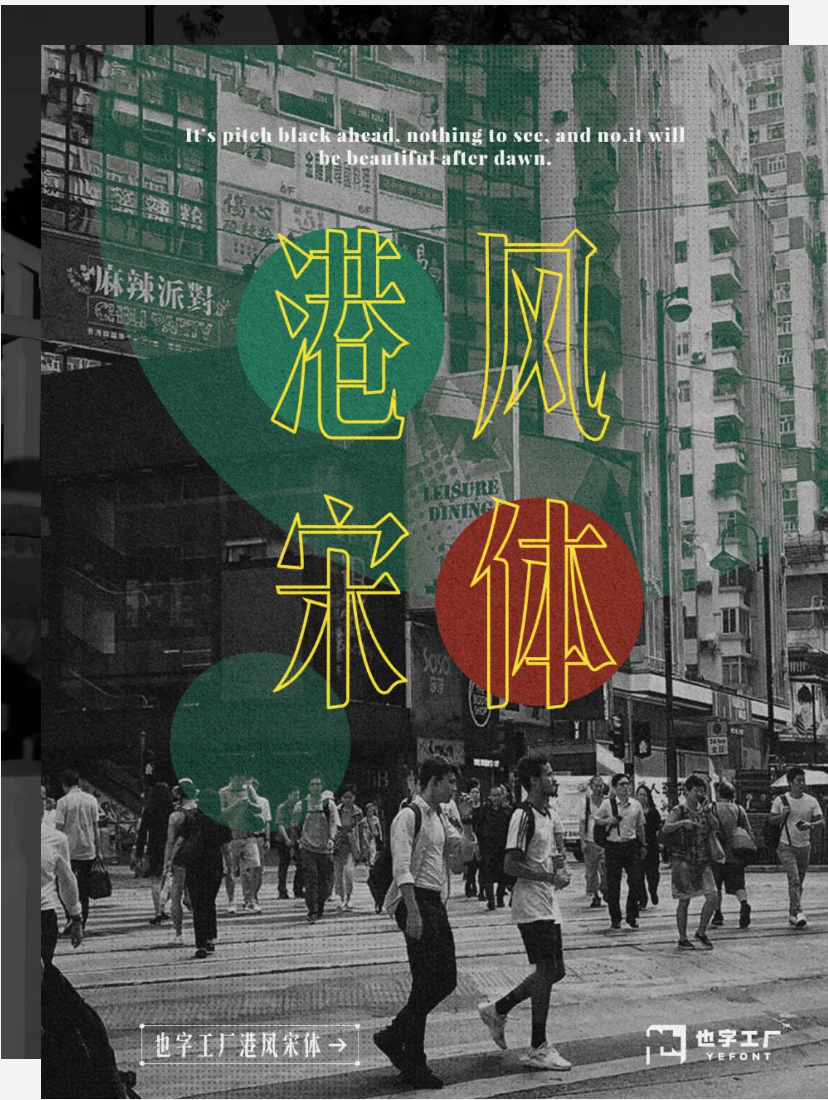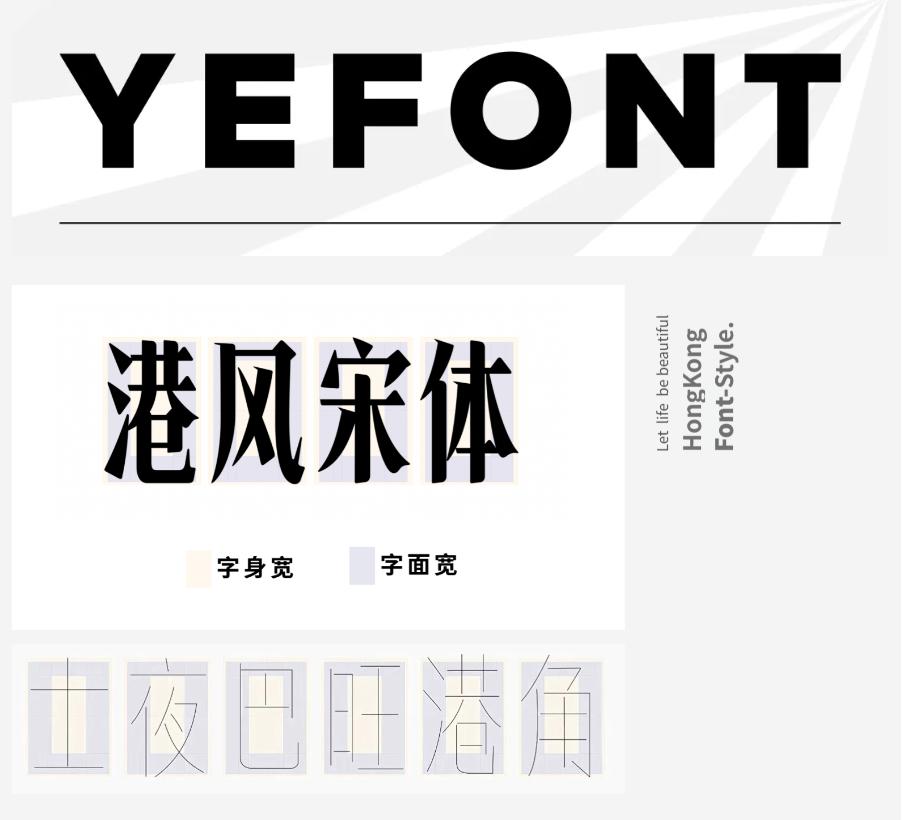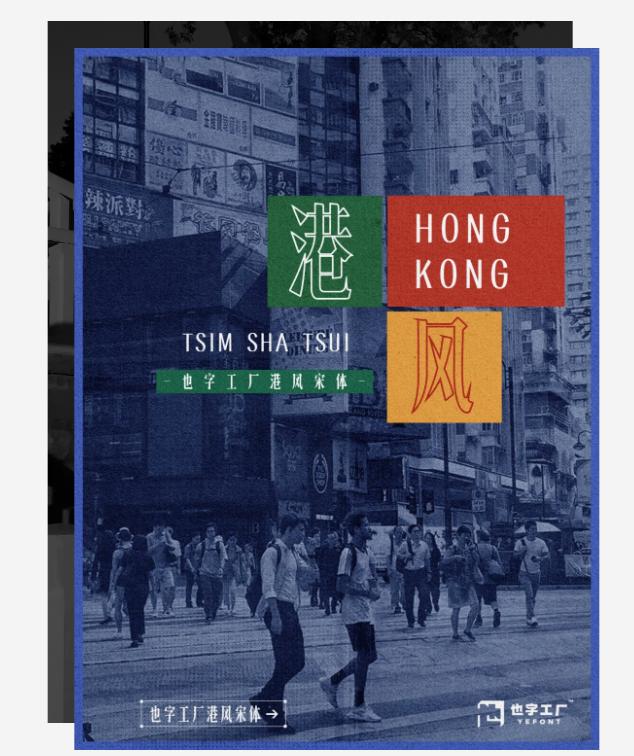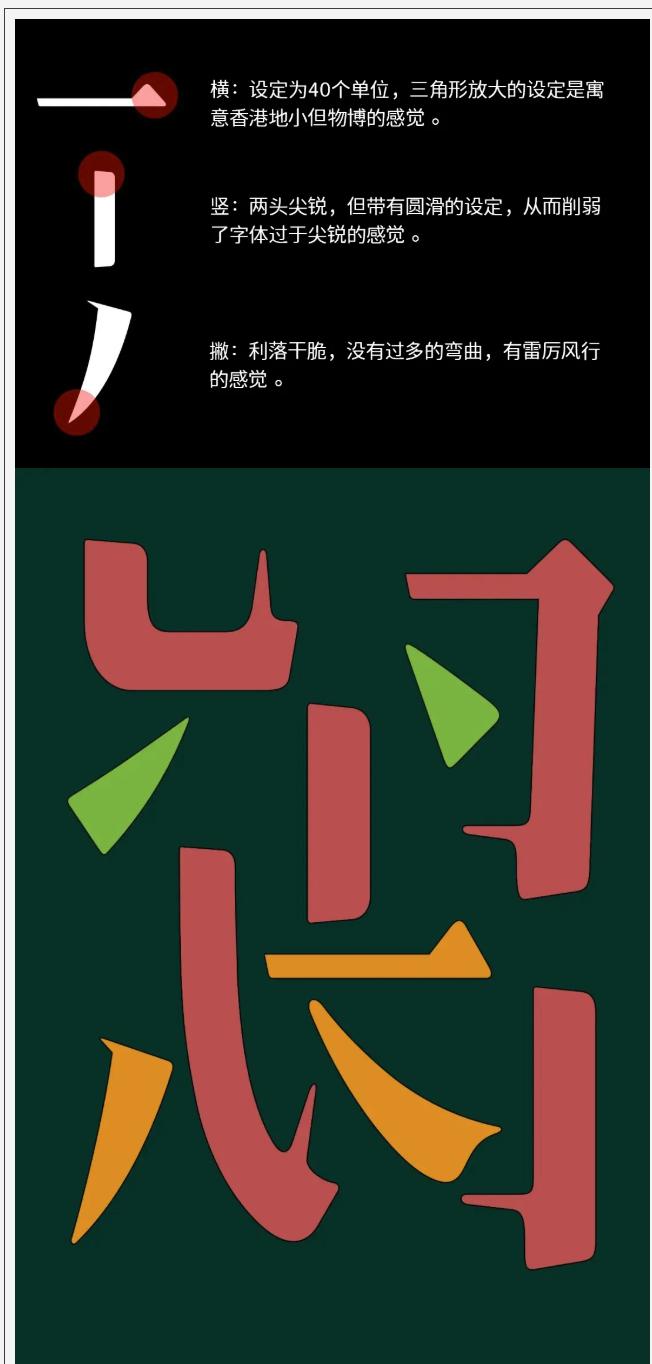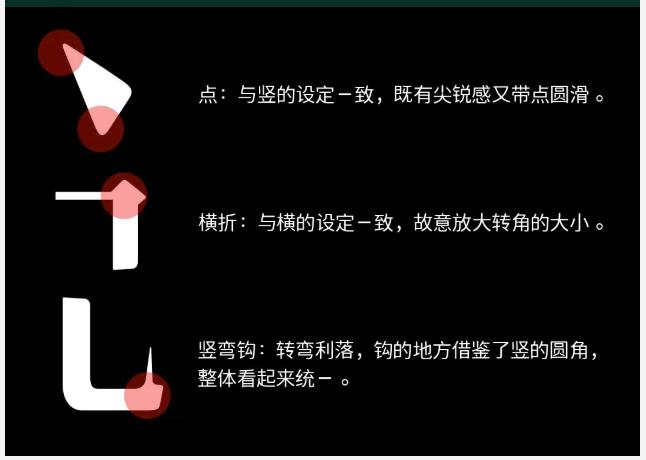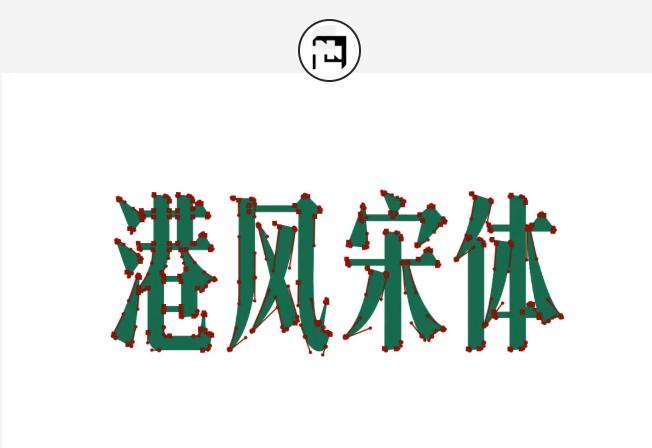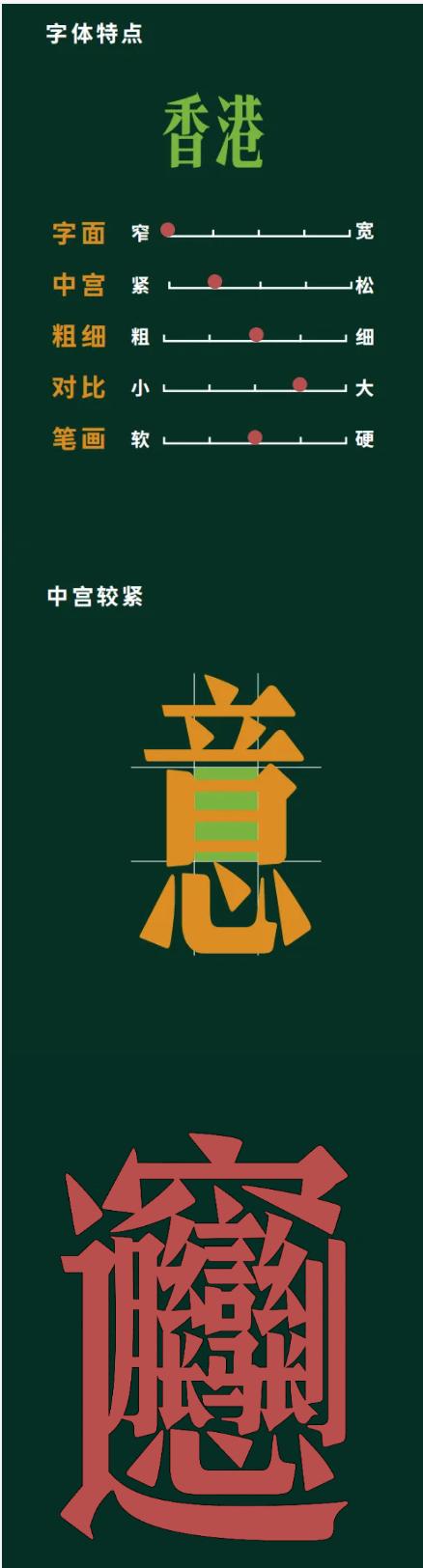
字体名称:也字工厂港风宋体
香港这座城市,它的独特性与生俱来。在历史长河中,香港在东西方文化交汇中独树一帜,既有民族性又有现代性的文化互渗与共融。对传统价值观、文化传承有着守旧而老派的认知和态度,同时也不乏前卫、先锋的思想和行为。这种传统与前卫的结合,塑造了香港独特的城市气质。
在香港,你可以看到高楼林立的城市景观,也可以看到洋溢着浓郁历史气息的街头巷尾。民间关系纵横交错,各阶层之间存在着深深的裂痕。然而,这样的混乱在香港却可以达到一种平衡,如同一幅有限而丰富的画卷,将人们的不同意识形态和信仰融合,将过去和现在交织,形成了别致的城市面貌。就是这样的香港,孕育出让全世界津津乐道的在地文化,从电影、文学、艺术、音乐划分出不同维度的时代隐喻齐头并进,成为几代人心目中如数家珍的经典记忆。
香港街头丨字体招牌丨图源网络
初衷&灵感
Let life be beautiful
HongKong
Font-Style.
作为一家具有独创性的字体设计品牌,也字工厂常年致力于探索和挖掘字体艺术文化领域的潜在价值和无限可能。我们一直密切关注着与字体紧密相关的文艺产业,并提供兼具创意和实用价值的字体服务。鉴于此,也字工厂即将面向市场推出新品字体——「港风宋体」。
在字体设计的过程中,也字工厂团队深刻意识到在选择港风宋体的定位时,「港风宋体」作为一种具有城市气质的字体,它应该能够体现出这座城市的文化特色、艺术底蕴和氛围。所以我们从香港电影中汲取了灵感,以电影海报的字体作为发力点,在投入了大量的时间、精力进行素材的收集与整合后,最终确定我们要呈现的字体特征——具有瘦长的外形特点,笔画纤细,横竖粗细对比明显,这种设计风格恰好迎合了港风文化所需要的特性。
特点&应用
出于对香港文化的喜爱和尊重,也字工厂希望通过「港风宋体」的设计作品来传达出这种情感,并反哺香港文化所带来的价值认同和审美共通。在市场上,虽然类似港风的宋体字已经存在,但与之形成鲜明对比的是「港风宋体」的笔触轻盈,让人能够领略到香港在不同时空下那股若有若无的文艺气息。
港风宋体是一款经过反复打磨和调整的美术宋体,设计精致且讲究。作为美术宋体,港风宋体可广泛应用于海报、招牌、站牌、文创等场景。其设计方向的独特之处,使得「港风宋体」在文化符号的呈现方面拥有强大的表现力。用「港风宋体」制作电影海报,可以更加贴近香港电影的特点,展现出香港电影的独特魅力;用「港风宋体」制作招牌,可以让顾客更直接地感受到香港文化的氛围;用「港风宋体」制作文创产品,可以为香港的文化传承增添一道亮丽的风景线。
我们希望它能够成为广大设计师们在海报、标志、出版物甚至装饰设计中的得力助手。我们坚信,港风宋体不仅仅是一种字体,它更代表着香港的多元魅力和文化内涵。让我们一起期待「港风宋体」的表现与使用,让它成为一个新时代的文化符号。